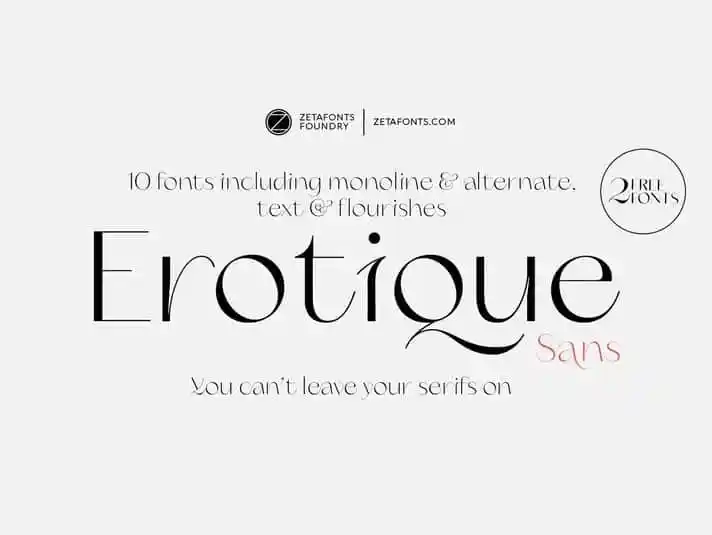
Erotique Sans Serif Font Demo – Fonte Grátis
Erotique Sans Serif Font Demo
Introduzimos a fonte Erotique Sans Serif, versão romana do Erotic typeface, que evoluiu do design original de Lovelace misturando suas curvas românticas com o aspecto glitchy e fluido da tipografia moderna e progressista neo-brutalista. O objetivo foi criar um estilo feminino mas assertivo e consciente. Esta font foi projetada por Cosimo Lorenzo Pancini e Maria Chiara Fantini, com a ajuda de Solenn Bordeau. Ainda que seja uma versão romana da fonte, Erotique Sans Serif traz algo inovador para o mundo das fuentes sans serif. Suas linhas finas e retas capturam o essencial do design moderno enquanto mantêm as características femininas assertivas de seu irmão gêmeo lovelace. É uma escolha perfeita para aqueles que procuram um equilíbrio entre seriedade e elegância, criando um design atemporal e contemporâneo.